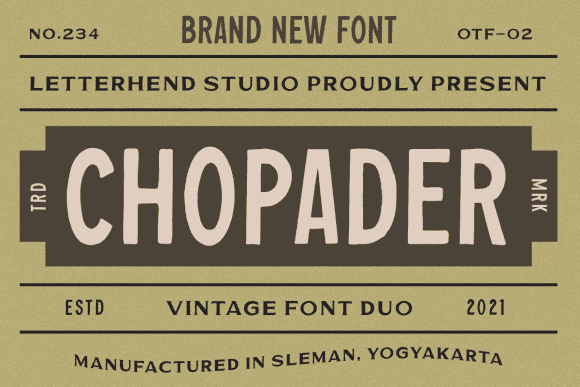
Название: Chopader Font
Chopader является смелым и старинным стилизованным шрифтом дисплея.
Он будет выглядеть потрясающе на любой плакатной листовке или принтере.